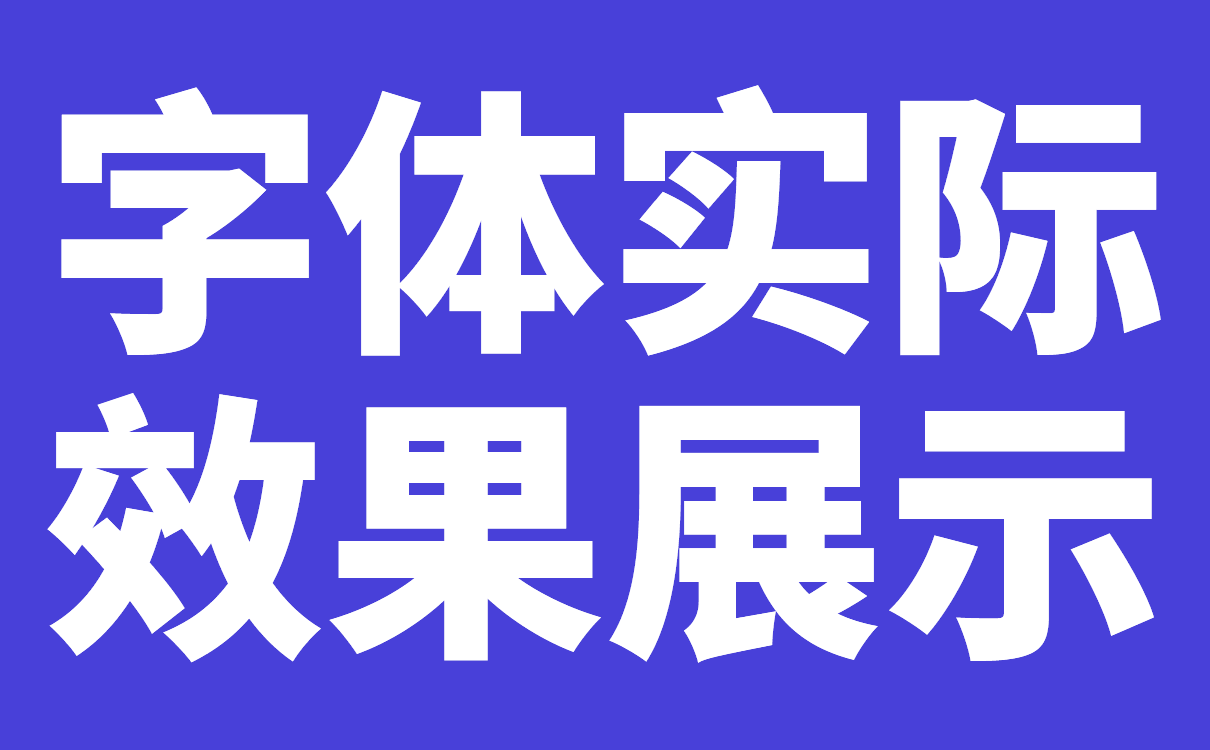
思源黑体 (行高修正版)
原版思源黑体的定界框比一般字体的大很多,这导致在 Photoshop、Illustrator 等软件中使用时,文本框下方会出现一段多余的空白。甚至当选中文字时,选区(反色区域)会遮盖住下一行的内容。这都对使用造成了一定的困扰。
此修正版基于 Adobe 官方发布的 SC 版修改,SC 版的文字写法遵循中国内地标准,且字数齐备,支持简体中文、繁体中文、日文、韩文等,适合中国内地用户使用。
我们修改了字体中 head 和 CFF 两个表中的定界框数值,没有改动任何其他内容,可放心使用。